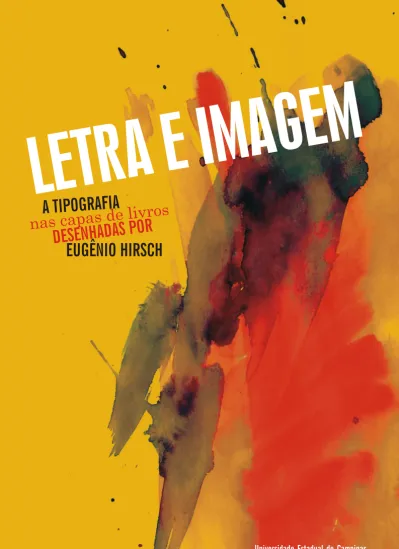
LETRA E I
A TIPOGRAFIA
MAGEM
nas capas
de livros
DESENHADAS P
OR
EUGÊNIO HIRSCH
L
ETRAEI
MAGEM: A
TIPOGRAFIANASCAPASDELIVROSDESENHADASPOR
E
UGÊNIOH
Eugênio Hirsch (Viena, 1923 - Rio de Janeiro, 2001) é mais conhecido por seu trabalho na editora Civilização Brasileira na primeira metade da década de 1960. Sua atuação na editora do Rio de Janeiro foi marcada pela versatilidade de recursos visuais e pela ampla liberdade concedida pelo editor Ênio Silveira. No mesmo período produziu capas para a editora Globo, de Porto Alegre, em quantidade muito inferior, mas com a mesma liber-dade e qualiliber-dade.
Após passagem pelos EUA, Hirsch foi contratado pela editora madrilenha Codex como diretor de arte da Coleção Museus do Mundo, e retornou ao Brasil no final dos anos 1960, passando a trabalhar para a Livraria José Olympio Editora.
Esta dissertação tem como tema central a relação entre o lettering e as imagens no trabalho de Hirsch. Essa relação é estudada a partir da análise das capas de livros produzidas por Hirsch entre 1959 e 1976. Dentro dessa amostragem abrangente são identificadas as caracterís-ticas mais marcantes e recorrentes do desenho de letras nas capas do designer austríaco.
Também é apresentada uma pequena amostra da produção de alguns capistas que atuaram no Brasil nas décadas de 1930, 1940 e 1950, fornecendo uma visão mais acurada da importância do trabalho de Eugênio Hirsch.
Eugênio Hirsch (Vienna, 1923 - Rio de Janeiro, 2001) is best known by his work for the publishing house Civilização Brasileira in the first half of the 1960s, wich was marked by a large range of visual resources used with great freedom granted to him by editor Ênio Silveira. In the same period he made book covers for Globo, a publishing house based on the city of Porto Alegre. Although less expressive in number, these covers kept the same quality and freedom.
After a short period in the USA, Hirsch was hired by Madri based publishing house Codex as art director, being responsible for El Mundo de los Museus collection. When returning to Brazil in the end of the 1960s, he begun to work for Livraria José Olympio Editora, in Rio de Janeiro.
This research is centered in the relation between letters and images in Hirsch’s book covers. This relation is studied by analizing the book covers made by Hirsch between 1959 and 1976. In this wide sampling, the most relevant and recurring caractheristics related to lettering and type in Hirsch’s work are identified.
Also presented is a sample of the graphic work done by some cover artists that had worked in Brazil during the 1930s, 1940s and 1950s, allowing a more accurate perception of the importance of Eugênio Hirsch’s work.
Chegando ao Brasil em 1957, o austríaco mudou-se para o 63
Rio de Janeiro em um período de efervescência cultural. As artes plásticas absorviam o impacto do Concretismo e do Neo Concretismo, e o Rio logo deixaria de ser a capital federal, lugar destinado a Brasília, cuja construção mexia com o país e provocava debates também no campo da arquitetura. Fernando Paixão, organizador de Momentos do Livro no Brasil, resume o panorama de agitação no campo político e cultural na passagem dos anos 1950 para os 1960: